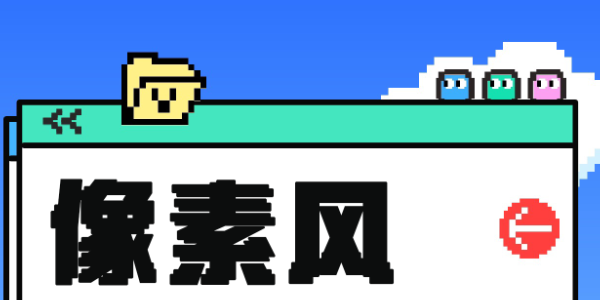
10款创意像素风字体,带你营造复古未来感
像素风字体也常被称为点阵字体,是一种在极简的方块网格中用像素点排列来拼凑出形态的字体,一个字符由许多这样的像素点组成。这种特性使得像素风字体拥有明显的锯齿边缘,几乎都由直线与直角构成,轮廓清晰但显得不够圆滑。
像素字体的迷人之处在于,它完美地融合了技术的限制与艺术的自由。它既承载着早期数字时代的集体记忆,又作为一种独立的、富有生命力的美学风格,持续地为现代设计注入灵感。像素风字体的发展历史使得它能营造出复古与科技感并存的独特氛围,在游戏界面与宣传(特别是像素风游戏)、科幻主题的影视、复古电子音乐、活动运营海报等主题中都能得到良好的应用。
本期就分三类主题,为大家介绍10款不同风格的像素风格字体~
一、科技感像素风字体
不同于传统像素字体的规整,科技感像素风字体并不是严格意义上的点阵字体,而是大量使用锐角、尖角和斜切面,创造出锋利、速度感强的外形,在复古与科幻的碰撞中,创造出一种独特的、自洽的美学语言。
这类字体常见于电竞、科幻游戏、赛博朋克主题、科技产品品牌、电子音乐、航空航天等领域,是“未来感”设计的首选视觉语言。
1. 点字像素之城
点字像素之城以复古像素风为核心,融合卡通趣味与科技质感,笔型以像素点为基本单元拼合,方头笔画搭配均匀粗细线条,连接处以颗粒感断开,既保留8-bit复古游戏的方块美学,又通过像素颗粒传递灵动趣味。无论是打造怀旧主题视觉,还是凸显科技潮玩风格,都能以独特像素语言赋予作品吸睛表现力。
1. 汉仪像素入侵
汉仪像素入侵以黑体为基础骨架,将部分笔画像素化,模拟像素块入侵黑体的趣味效果。方块字形,主笔清晰规整,像素“入侵”斜向、弧线笔画,以及部分横竖笔画的末端。以创新的设计手法玩转复古像素风格,趣味十足。兼容复古风格和创新风格,相较于传统像素字体,这款字体作为视觉元素有着更好的可识读性,有着更广泛的应用可能。
二、传统点阵像素字体
早期电子游戏的出现,受限于极低的屏幕分辨率,显示文字必须使用像素点阵,像素字体应运而生。随着个人电脑和8-bit/16-bit游戏机(如任天堂红白机)的普及,像素字体成为主流,与《超级马里奥》等经典游戏一同定义了那个时代的视觉语言。
这类字体更适合营造千禧年的复古氛围,用于需要表达复古未来感的设计中,也是怀旧风格游戏界面、像素艺术设计的首选字体。
1. 点字像素16
点字像素16基于黑体字形进行像素化,字重较粗,在每个像素点之间加入了白线来区隔像素点,使其更有传统屏幕上所显示的像素字体的感觉,复古氛围十足。
1. 破晓像素
破晓像素是一款开源的免费商用的像素字体,是基于Fairfax、ZLabs Bitmap和Galmuri三款经典开源像素字体合并而成的“字体集合”。它采用标准像素网格构建,笔画横平竖直,呈现出清晰的点阵化特征和独特的机械感。在保持复古感的同时,通过优化的字符间距和比例设计,确保了在低分辨率屏幕上也能有舒适的阅读体验。
1. 汉仪像素9px
汉仪像素9px是一款像素风格的中文字库,大小为9x9像素。区别于常规像素字体仅留有1像素的间距,左右各保留1像素的间距,即2像素的间距,以优化排版效果。采用黑体的设计思路,笔画更加简洁明朗,布白均匀,灰度平衡。注重轮廓的保留和线条的流畅,采取避让、合并、精简的方式,使整体更贴近常规字形,同时具有强烈的像素风格。适用于像素环境,如点阵显示屏、游戏机或其他特殊使用场景,也适用于当下流行的复古风格。
1. 缝合怪像素字体
缝合怪像素字体也是一款开源免费商用的像素字体,它是经典的黑体无衬线风格,字形结构清晰,没有多余的装饰,保证了在低分辨率下的识别度。字体尤其适合为复古风格的像素游戏提供完整的文字解决方案,尤其适合用于游戏UI、对话和菜单等。
1. 字体管家波点
Aa字体管家波点是一款略显另类的像素字体,是一款由圆点构成的创意美术字。风格偏向波普艺术,具有活力和趣味性,字形流畅、圆润、充满动感。会让人联想到霓虹灯招牌,很有赛博朋克的感觉,适合想要营造活泼、时尚、潮流感的设计场景,例如派对海报、潮流品牌视觉设计。
三、创意像素风字体
创意像素风字体都打破了像素字体只能是规整、方块、尖锐的刻板印象,将楷体、圆体、勘亭流字体融合像素风格,打造出新奇的视觉语言。
这类像素字体更活泼多变,适合用于活动运营、banner、电商海报、饭圈周边文创设计等年轻化的设计场景中使用。
1. 点字像素啵啵
点字像素啵啵的字体设计融入像素点的概念,巧妙运用圆角组合字体,根据不同字型展现字体的形态各异,俏皮有趣。在传统像素字体的方正骨架上,笔画两端和转角都引入了圆润的曲线处理,让硬邦邦的方块变得Q弹可爱。圆角的运用让原本离散的像素点连成一个个整体,形成了独特的“块面感”。加上圆润的笔画,字形显得形态各异,增添了天真、好玩的氛围。这种设计让“点字像素啵啵”自带装饰效果,哪怕只用一个词,也像一件精心设计的视觉作品,很适合作为设计中的视觉焦点。适合用于追求萌系、可爱、趣味感的设计,如儿童产品、甜点饮品、趣味游戏UI和活动海报。
1. Aa像素江户
Aa像素江户以经典的勘亭流字体为骨架,用像素的手法重新演绎,打造出一种兼具历史温度与现代感的独特风格。它融合了日式古典招牌美学与现代像素风,拥有非常独特的视觉个性。字体延续了勘亭流字体笔画粗壮、形态饱满的特点,视觉冲击力很强,将毛笔书写的粗犷随性与像素的电子复古感结合在一起,在低分辨率的像素网格上,勾勒出了江户时代的豪放。
同时,这款字体也是一款家族字体,拥有少有的空心像素字体。Aa像素江户-影通过外描边反白和像素错位,创造出白字带阴影的立体感,装饰性更强。
1. Aa像素山海
Aa像素山海是一款将传统楷书风骨与像素点阵科技感巧妙融合的创意中文字体。它在复古的像素骨骼里,注入了手写书法的神韵。字体整体风格厚重饱满,线条简约优美,以手写书法字体为原型,融入了楷书的笔意,又融入像素点设计,用最现代的技术语言,演绎了最传统的书写之美。能为设计增添一抹既复古又独特的文化气息,非常适合中式复古风的设计场景中使用。